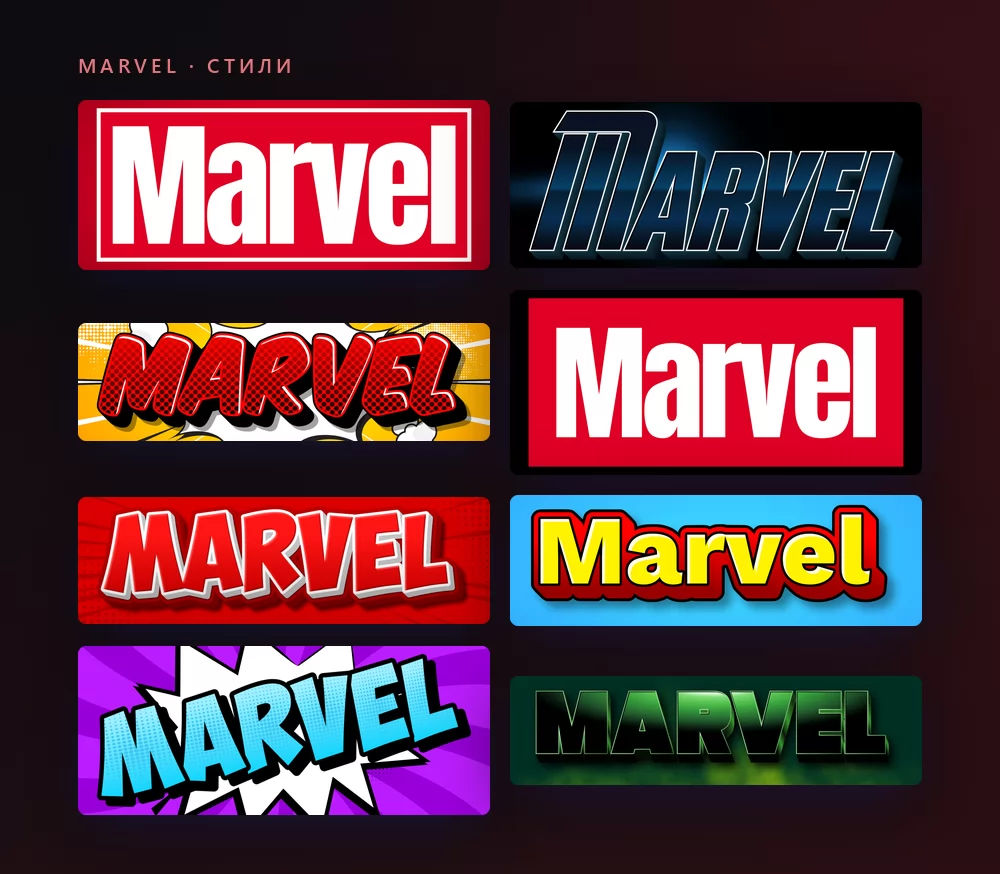
О шрифте Marvel
Marvel Comics - американское издательство, стоящее за Человеком-пауком, Людьми Икс, Железным человеком, Фантастической четвёркой и Мстителями. Его логотип один из самых простых во всей индустрии развлечений: слово, набранное белым, внутри красного прямоугольника, и больше ничего. Ни фаски, ни хрома, ни падающей тени. Весь эффект держится на жирности букв и на тесноте рамки.
Леттеринг очень близок к Benton Sans Extra Comp Black, нарисованному Сайрусом Хайсмитом и Тобиасом Фрер-Джонсом для Font Bureau. Это узкий гротеск: буквы сжаты по ширине и доведены до тяжёлого веса, поэтому короткое слово заполняет широкую полосу без единого декоративного штриха.
Стоит запомнить его силуэт, и тот же шрифт начинает попадаться в других местах: логотип Dressbarn и титульная карточка сериала Longmire набраны Benton Sans.
Прежде чем пробовать его воспроизвести, стоит знать две детали. Первая: версия логотипа изменена, а не набрана прямо из шрифта, в ней правили и сами формы букв, и толщину штрихов, и межбуквенные расстояния. Вторая - анатомическая. Присмотритесь к надписи: каждая буква, кроме E и L, касается соседней сверху или снизу. Это ручной кернинг, а не то, что шрифт делает сам, и именно поэтому установленный Benton Sans всё равно не даёт вам логотип.
Красный прямоугольник моложе самой компании. Marvel меняла свои надписи восемь десятилетий, прежде чем в редизайне 2002 года появился блок, и с тех пор его скорее подчищали, чем заменяли. Благодаря ему логотип одинаково хорошо держится и в размере почтовой марки на обложке комикса, и во всю стену кинотеатра.
Как сделать текст в стиле Marvel
Стиль на целевой странице - это сам логотип: белые прописные в красном блоке. В списке вокруг него собрана комиксовая сторона того же мира: растровые точки, вспышки речевых облаков, толстые контуры, хром и контровой свет. Можно также посмотреть весь набор текстовых эффектов Marvel и вернуться с тем, который понравился. На вкладке «Стиль» в любом из них меняются заливка, контур и тень.
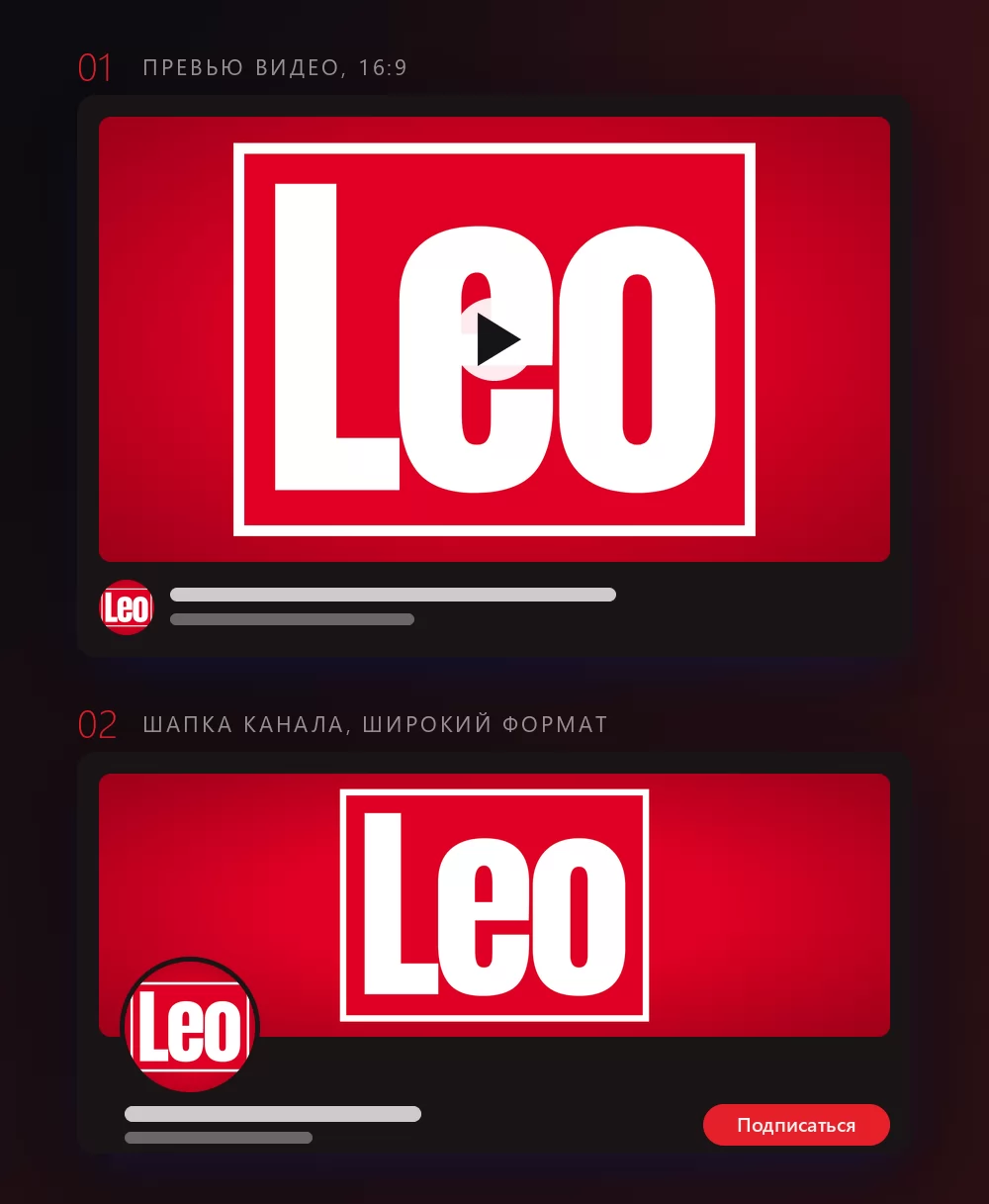
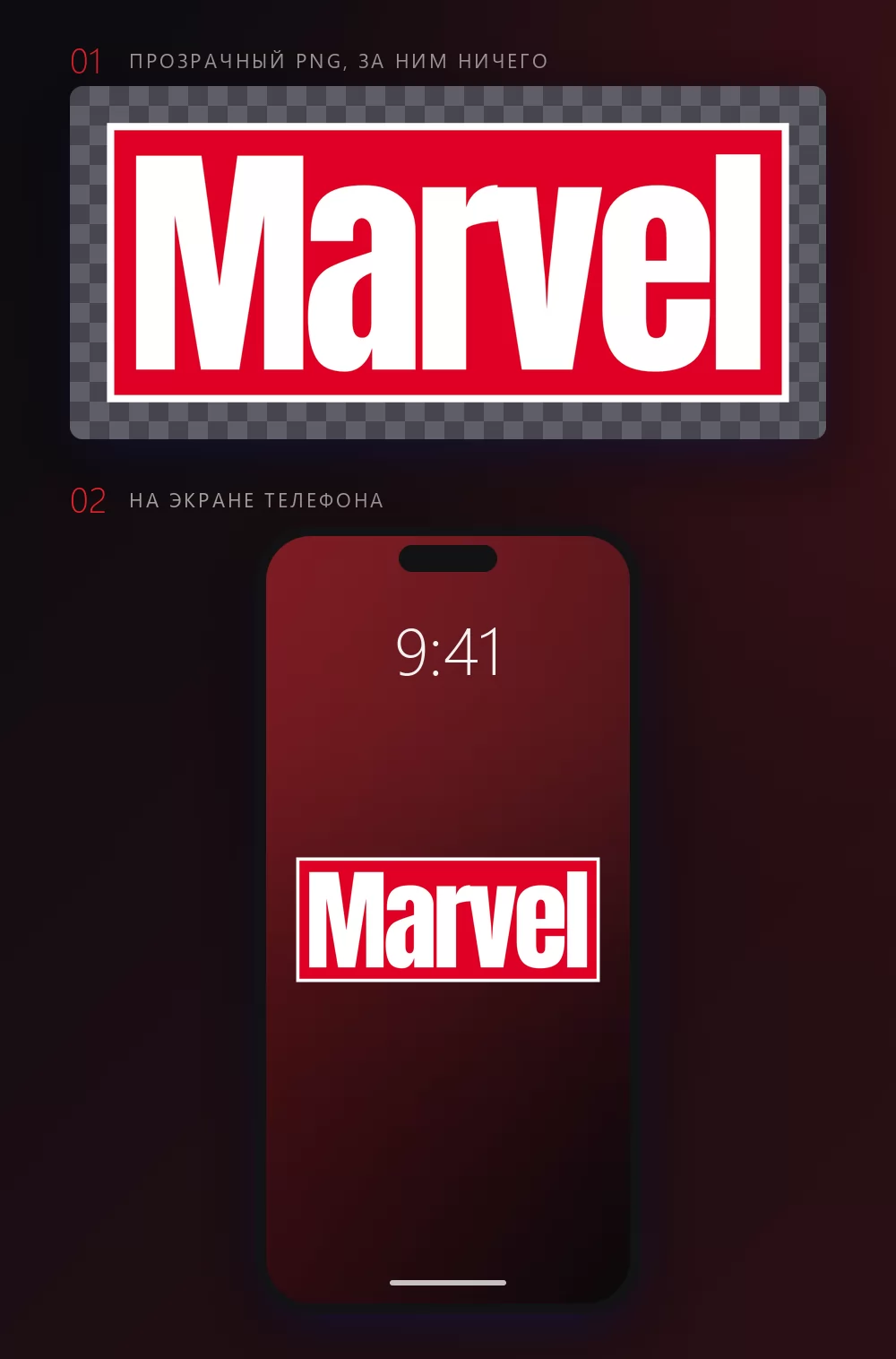
Что происходит, когда имя длиннее
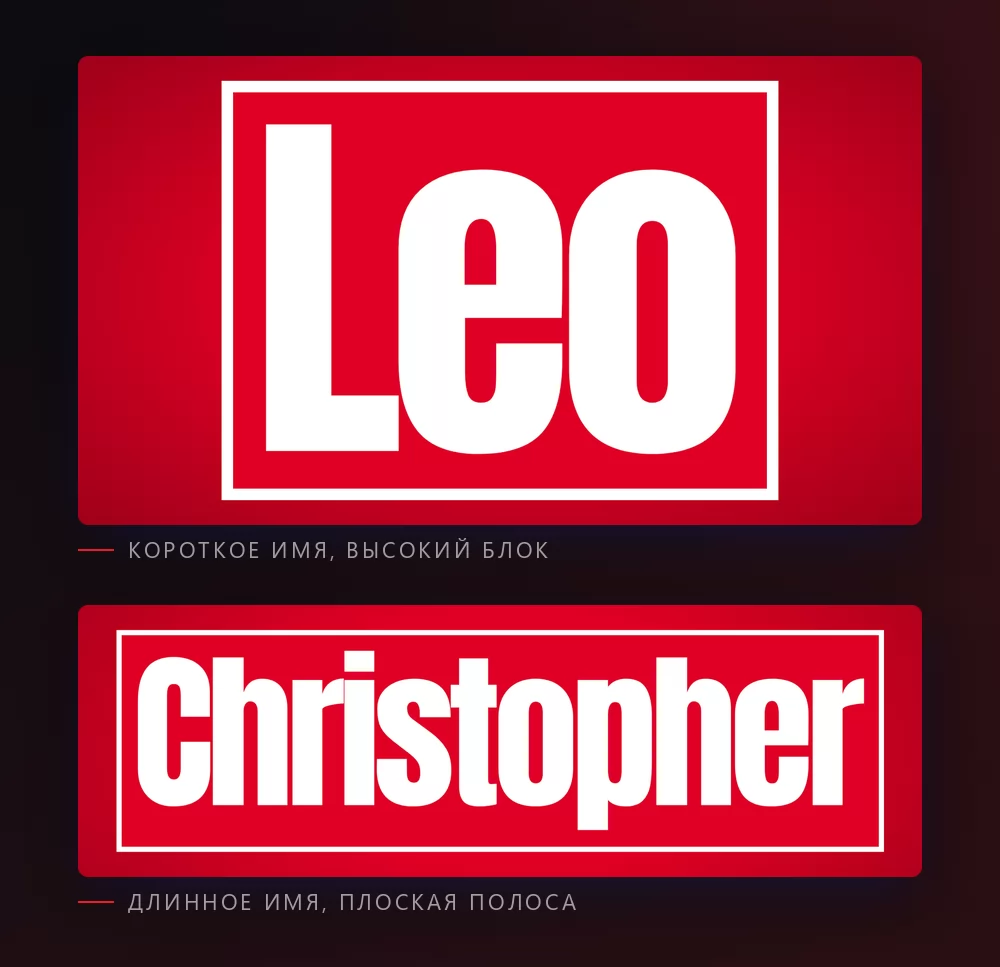
Мы это измерили, потому что от этого зависит, какое имя куда ставить. Красный блок никогда не переполняется. Наберите больше букв, и ничего не вылезет за рамку: блок расширяется до фиксированного предела, а дальше остаётся той же ширины и становится более плоским, а буквы уменьшаются, чтобы поместиться.
Значит, форму задаёт слово, а не какая-то настройка. Короткое имя даёт высокий, почти квадратный блок. Длинное имя даёт широкую плоскую полосу. Решает ширина слова, а не количество букв, поэтому два имени одинаковой длины могут получиться разными, если у одного буквы шире.
Пользуйтесь этим осознанно. Длинное имя уже имеет нужную форму для шапки канала или баннера. Короткое имя или инициал - то, что заполняет квадратную аватарку. Подобрать слово под место проще, чем потом воевать с местом.
Marvel Comics или Marvel Studios
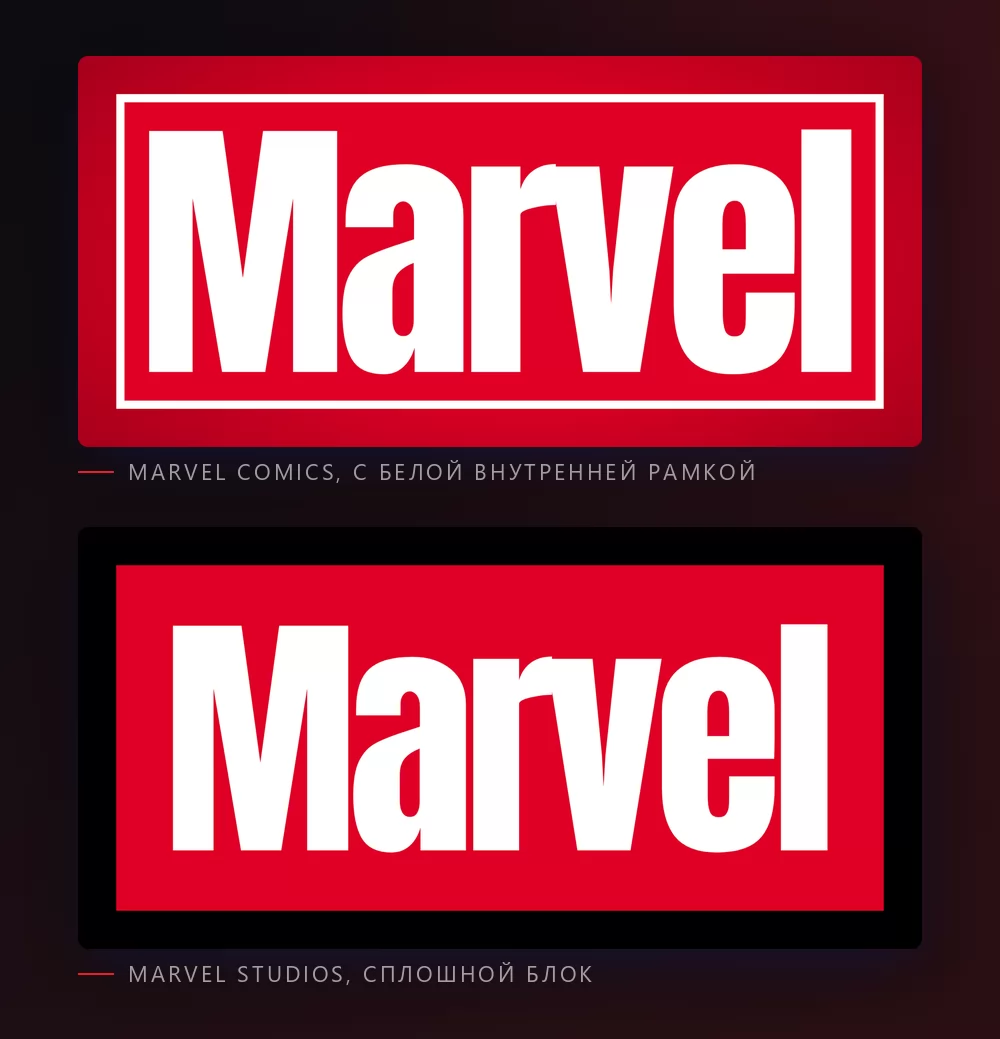
Люди набирают «логотип Marvel», имея в виду одно из двух, и разница ровно в одной линии.
У комиксового блока есть тонкая белая рамка, проведённая внутри красного поля, так что надпись сидит в обрамлённой панели. Это та версия, которую печатают на обложках комиксов, и именно она на целевой странице.
Сплошной блок обходится без внутренней рамки: красное поле, белые буквы, больше ничего. Это более простая и более кинематографичная версия, ближе к заставке, с которой начинается фильм Marvel Studios.